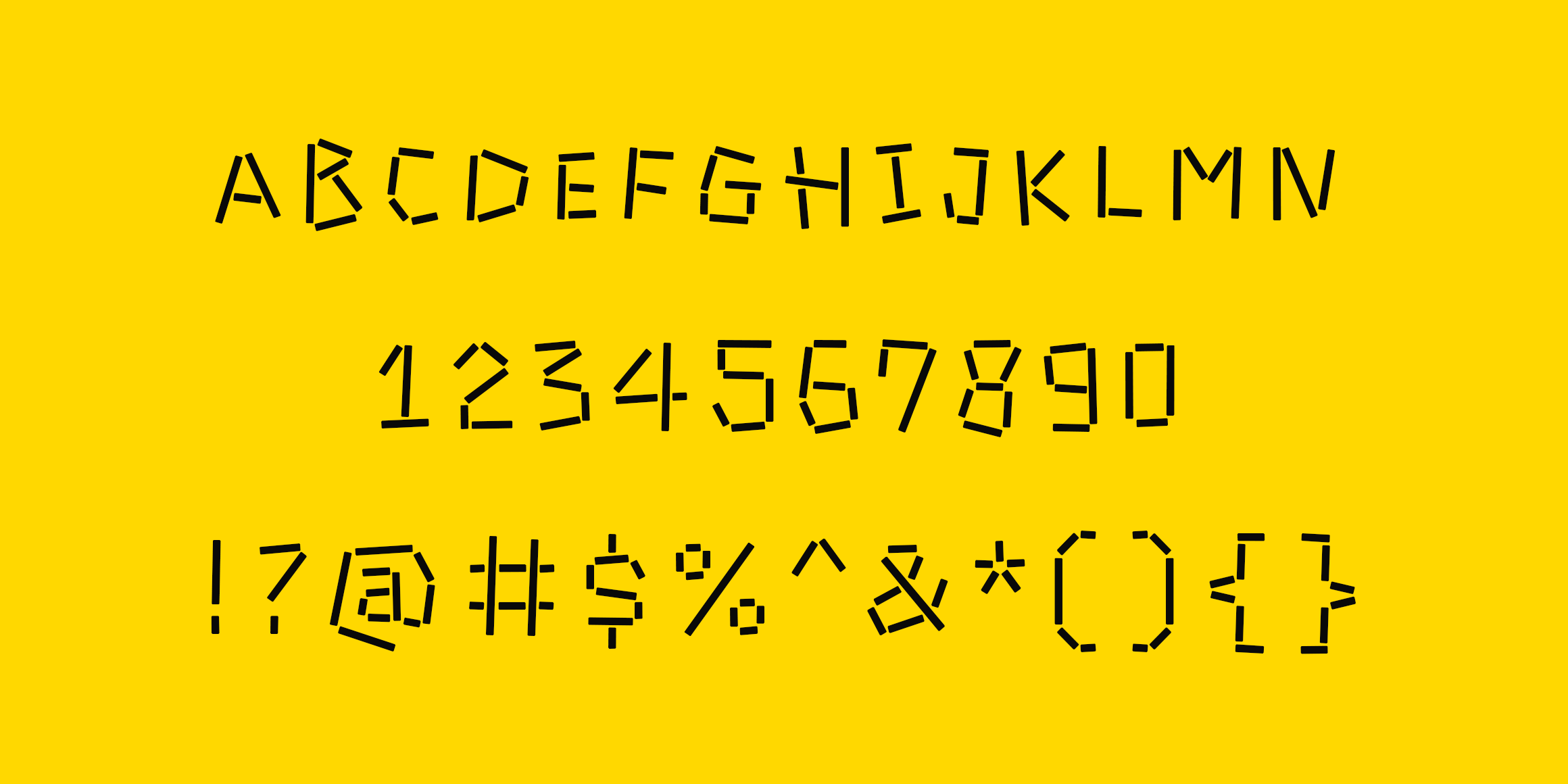
개별 스타일 나름대로 독특한 개성을 지니고 있고, 헤드라인, 로고, 브랜딩 작업에 사용하면 어떠한 한글 글꼴들과도 잘 어울릴 수 있습니다.
임의 합자(Discretionary Ligatures) : Ca, Co, Ga, Go, La, Lo, Oa, Oo, Pa, Po, ba, bo, ca, co, da, de, do, ea, fa, fo, gg, go, la, ll, lo, ly, mu, nu, oo, pa, po, rr, um, un